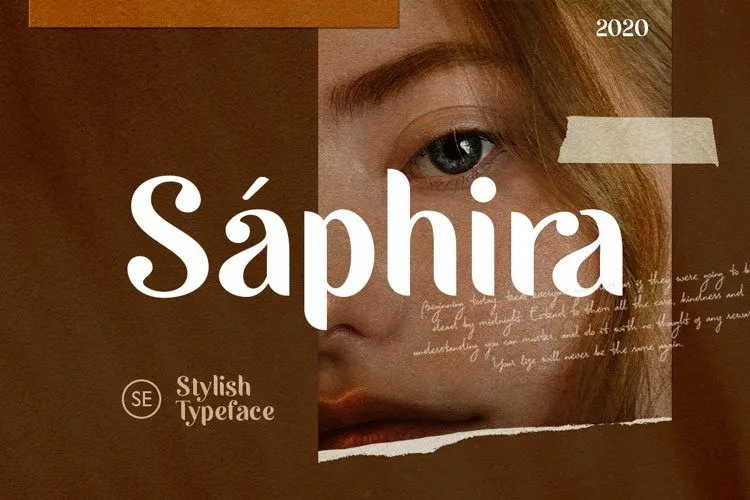
A Saphira é uma fonte sans serif moderna e elegante criada por Saridezra com várias ligaturas e alternativas que darão seu slide de apresentação, sua marca ou até mesmo seu convite para casamento um brilho ainda mais especial e destacado! Esta fonte também suporta múltiplas línguas e já está codificada com PUA. É perfeita para quem busca uma fonte que não só se destaca na apresentação de um evento ou produto, mas também oferece facilidade de uso em vários idiomas, tornando-a a escolha ideal para designers gráficos atentos aos detalhes.